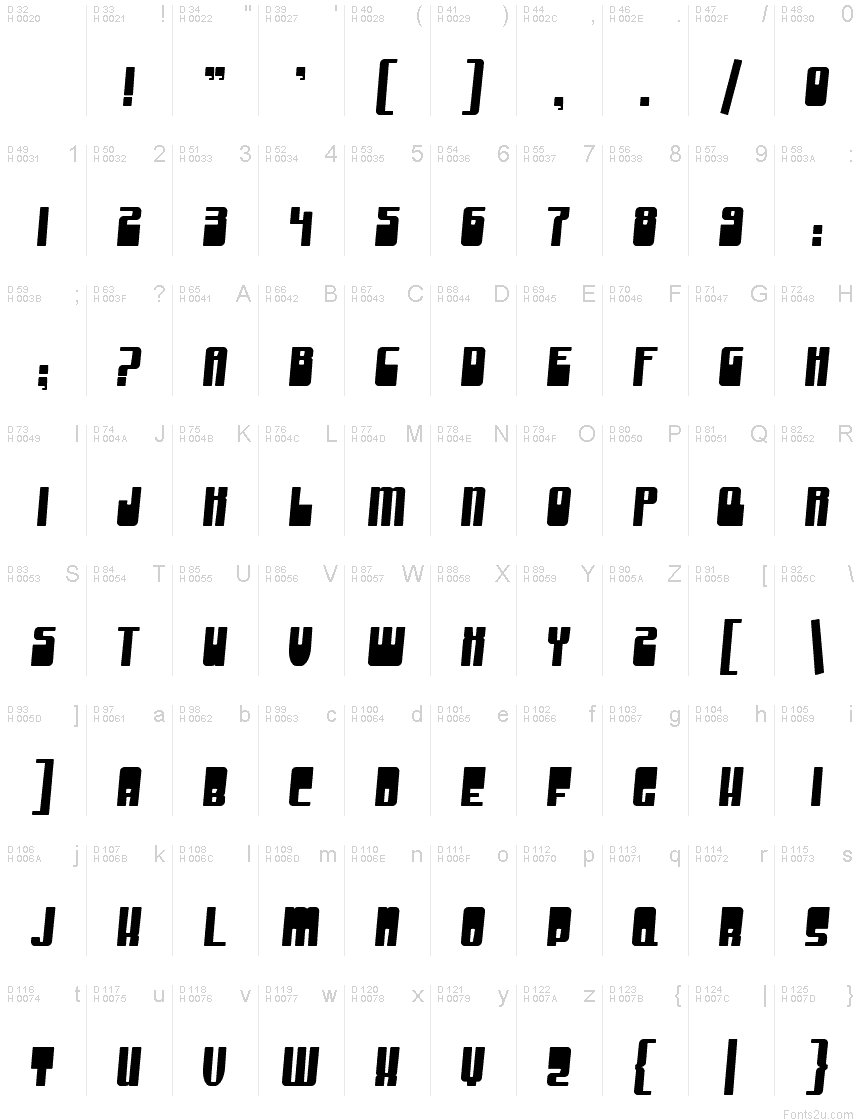
Krój Groove Machine od Shywedge to bezpłatny, groovy font typu display, który uderza z siłą linii basu – jest pochylony, dynamiczny i stworzony do ruchu. Jego odważne, blokowe kształty przypominają stosy kolumn głośnikowych, a ciasne odstępy i nachylenie w przód nadają każdemu słowu poczucie dynamiki i pędu. Zaokrąglone rogi dodają mu przyjaznego, funkowego charakteru, dzięki czemu nawet ciężkie, czarne litery wyglądają gładko, a nie surowo.
Groove Machine pozwala błyskawicznie nadać retro-klubowy klimat ulotkom, zaproszeniom na imprezy, okładkom albumów, identyfikacji wizualnej wydarzeń, miniaturkom na YouTube czy wyrazistym znakom firmowym. Ten bezpłatny font błyszczy, gdy użyjesz go w dużym formacie, zwłaszcza w wersji all caps i z mocnymi kolorami. W przypadku tekstów głównych lub drobnych detali, połącz go z prostym krojem bezszeryfowym, aby zachować czytelność, podczas gdy Groove Machine zajmie się przyciąganiem uwagi w Twoich nagłówkach.